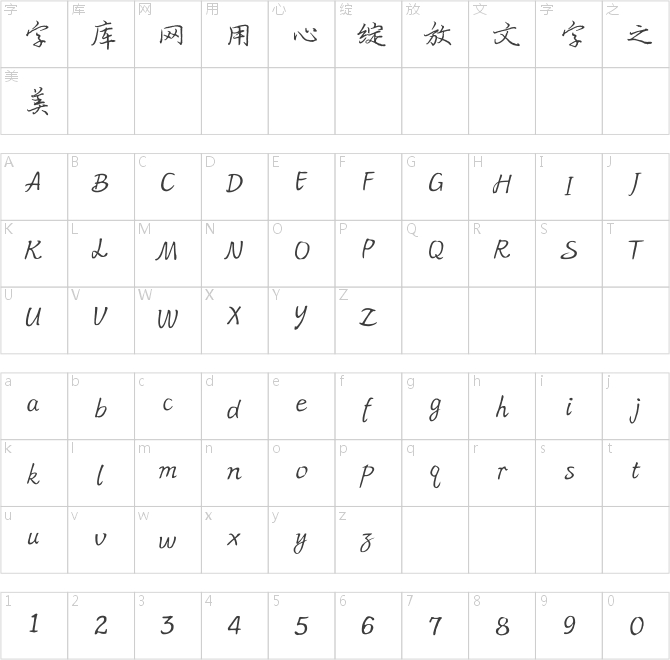
方正字迹-新式古风行楷
作者爱好书法并喜欢尊崇古法,但不拘泥于某个风格,对字的结构有个人深刻研究。该款字传承“中庸”思想,不张扬做作,继承古人同时取法今人审美。
方正字迹-新式古风行楷字体字库是一款让人赏心悦目、百看不厌的中文字体,适合各类广告和产品包装设计应用,字体大小8.22MB,格式为TTF字体,上传用户是雅锐广告李玥,作者/版权方为方正字迹